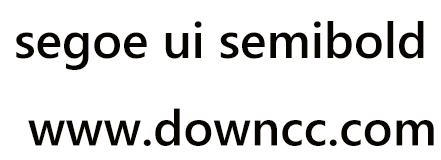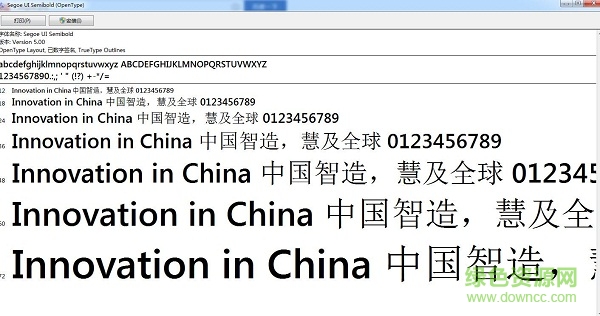
segoe ui semibold字體
segoe ui semibold字體是一款半粗體英文黑體字體,筆法挺勁,特征鮮明富有朝氣,整體制作非常細膩精良,可以用于高精度印刷產(chǎn)品,歡迎大家本站免費下載!
segoe ui semibold字體特點
橫平豎直字見方 ,大小粗細一個樣 ,上緊下松要記牢 ,筆畫穿插又避讓 ,自隙均勻要講究 ,整齊美觀又大方